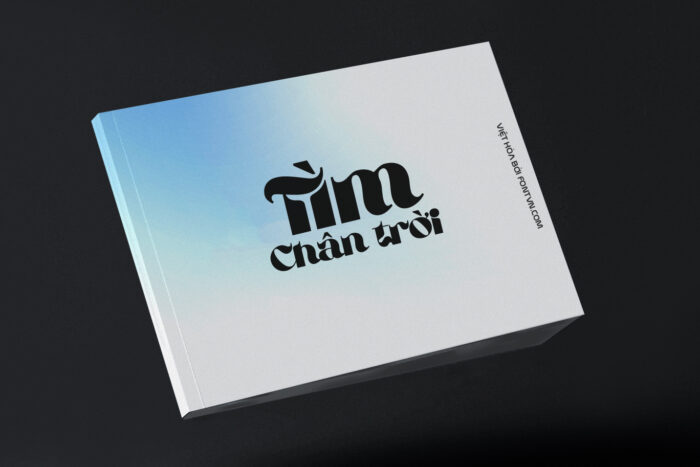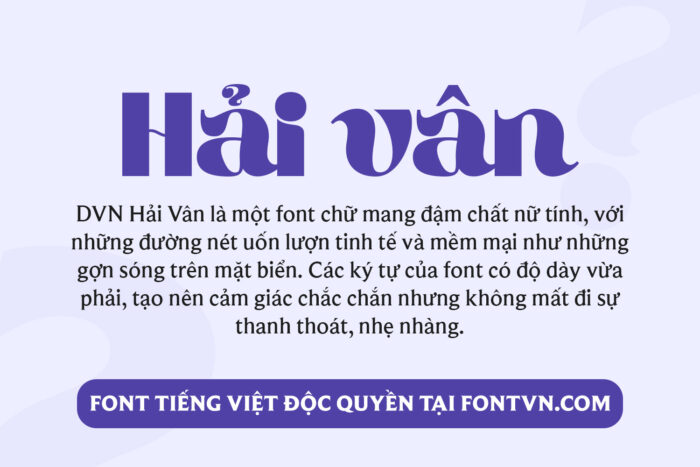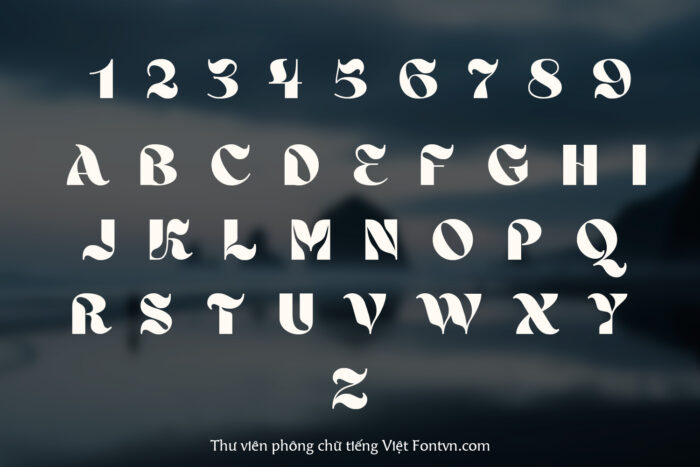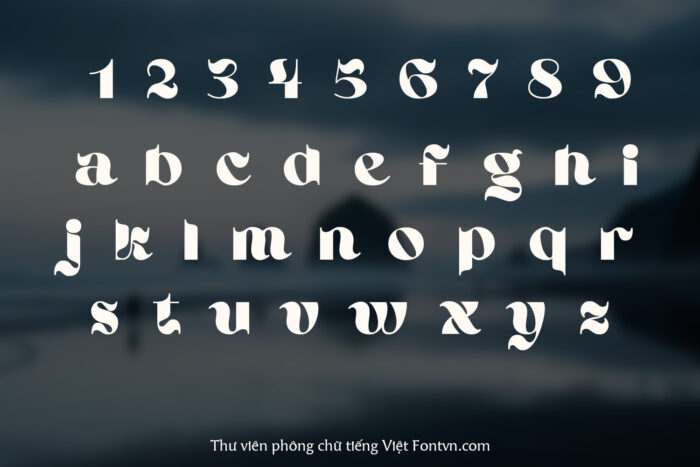
DVN Hải Vân – Font chữ uốn lượn tinh tế và mềm mại phù hợp theo xu hướng mới nhất
DVN Hải Vân là một font chữ mang đậm chất nữ tính, với những đường nét uốn lượn tinh tế và mềm mại như những gợn sóng trên mặt biển. Các ký tự của font có độ dày vừa phải, tạo nên cảm giác chắc chắn nhưng không mất đi sự thanh thoát, nhẹ nhàng. Điểm nhấn của DVN Hải Vân nằm ở những nét cong mềm mịn, mang đến phong cách quyến rũ và đầy sức sống.
Phong cách của font này rất phù hợp cho các thương hiệu mỹ phẩm, thời trang cao cấp, hoặc các sản phẩm liên quan đến phong cách sống sang trọng. Sự uyển chuyển trong từng chi tiết của font chữ dễ dàng tạo ra sự liên kết mạnh mẽ với phái đẹp, từ đó nâng tầm thương hiệu, giúp truyền tải thông điệp về sự tinh tế và đẳng cấp.
DVN Hải Vân có thể ứng dụng trong thiết kế logo, bao bì sản phẩm mỹ phẩm, quảng cáo, và các ấn phẩm thương hiệu hướng đến sự sang trọng và thanh lịch.